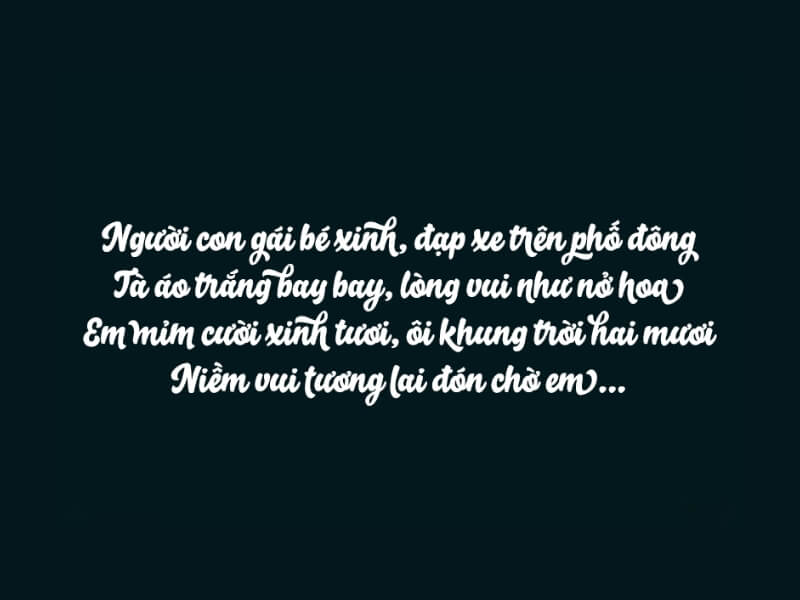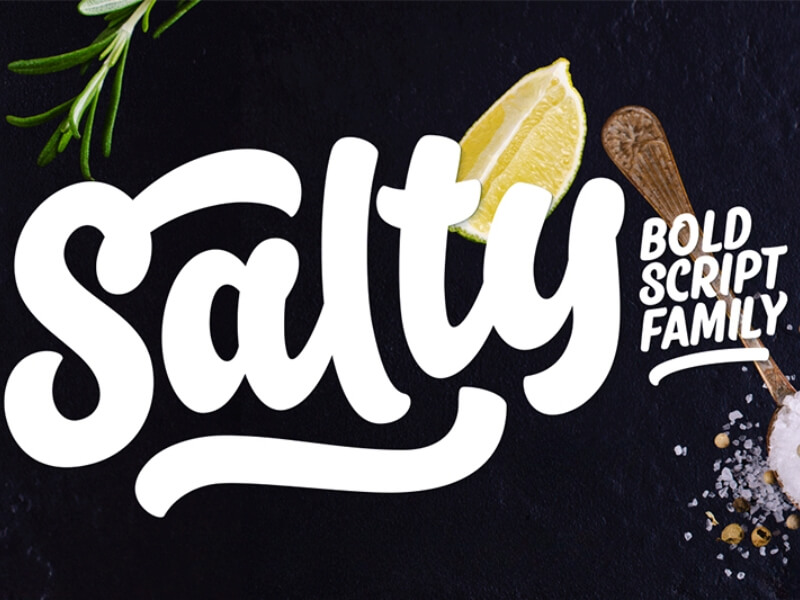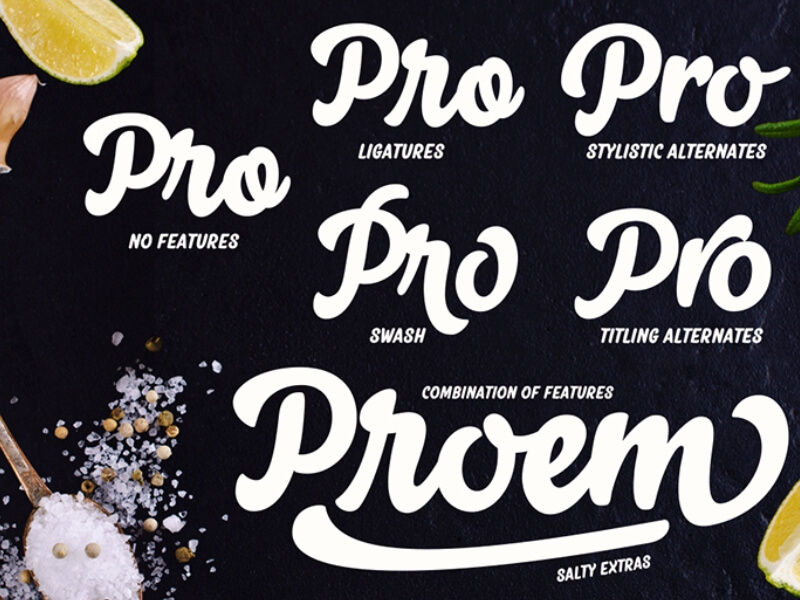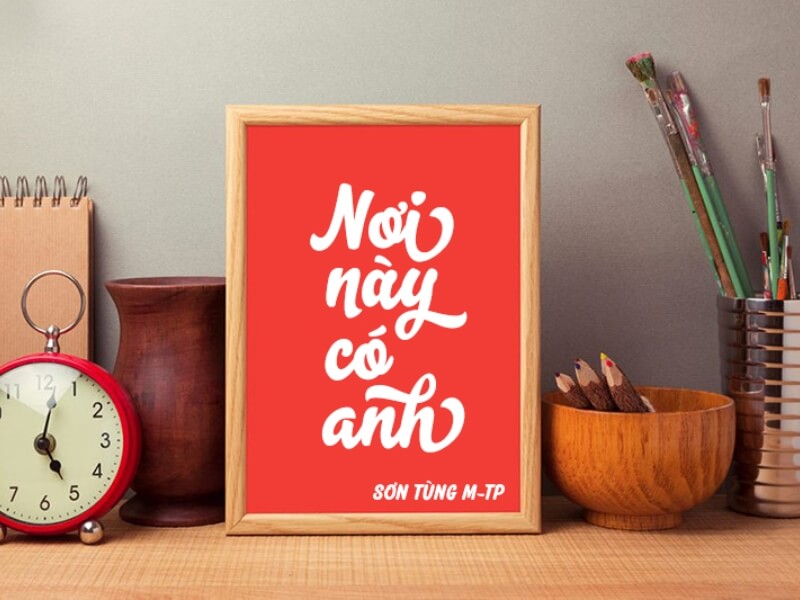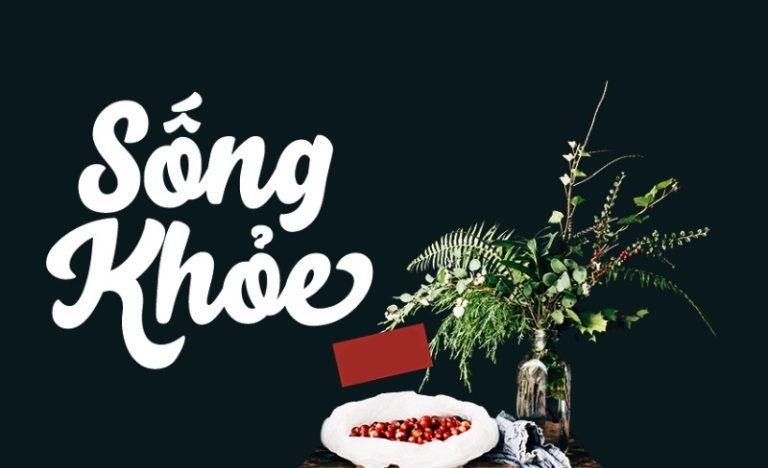
Font Việt hóa SVN Salty Script mang phong cách brush script với những đường nét thô mộc, tạo cảm giác như được viết bằng cọ vẽ đầy ngẫu hứng. Đây là bộ font chữ sở hữu nguồn năng lượng trẻ trung, phóng khoáng, phù hợp cho những dự án thiết kế hướng đến sự tự nhiên và gần gũi. Thư viện tài nguyên của BCD House chia sẻ bộ font này nhằm hỗ trợ cộng đồng kiến trúc và thiết kế có thêm lựa chọn chất lượng để làm mới các ấn phẩm đồ họa cũng như nhận diện thương hiệu.
Khám phá vẻ đẹp phóng khoáng của font Việt hóa SVN Salty Script
Điểm thu hút của SVN Salty Script nằm ở cấu trúc chữ không quá gò bó, các nét đậm nhạt được xử lý khéo léo như vệt mực loang trên giấy. Khác với các dòng font script thanh mảnh, Salty Script mang đến vẻ ngoài dày dặn, vững chãi nhưng vẫn giữ được sự linh hoạt cần có. Việc sử dụng bộ font Việt hóa SVN này giúp các designer hạn chế tình trạng lỗi hiển thị ký tự đặc trưng trong tiếng Việt, giúp quy trình làm việc trở nên thuận tiện hơn.
Bản Việt hóa đã được tinh chỉnh để các dấu thanh phối hợp hài hòa với độ cao của từng ký tự. Nhờ đó, tổng thể văn bản sau khi trình bày mang lại cảm giác cân đối, dễ nhìn và có tính thẩm mỹ cao. Đây là yếu tố quan trọng giúp nâng cao hiệu quả thị giác cho người xem trong các bản vẽ phối cảnh hoặc thiết kế bao bì sản phẩm.
Tư vấn phối màu: SVN Salty Script thường phát huy hiệu quả thị giác cao khi sử dụng các tông màu đất, xanh rêu hoặc các màu pastel trên nền trung tính. Bạn nên giữ nguyên nét chân thực của vệt cọ vẽ bằng cách hạn chế các hiệu ứng đổ bóng quá phức tạp.
03 Ứng dụng font Việt hóa SVN vào không gian kiến trúc
Với đặc tính nghệ thuật và sự tự nhiên, SVN Salty Script được nhiều kiến trúc sư và chủ đầu tư ưa chuộng để tạo điểm nhấn cho các công trình mang tính chất thư giãn:
- Bảng hiệu Homestay ven biển hoặc vùng núi: Phong cách brush của font chữ này rất ăn ý với các vật liệu tự nhiên như gỗ, đá hay mây tre lá. Đây là lựa chọn phù hợp cho biển hiệu các khu nhà lắp ghép, homestay container giúp tạo cảm giác mộc mạc và thân thiện cho du khách.
- Ấn phẩm truyền thông cho dự án nghỉ dưỡng: Sử dụng Salty Script cho các tiêu đề trên brochure, banner quảng cáo giúp khơi gợi cảm hứng về một không gian sống tự do, không khuôn khổ, rất dễ tạo thiện cảm với khách hàng.
- Trang trí nội thất và Quotes treo tường: Bạn có thể dùng font chữ này để cắt decal hoặc uốn đèn led trang trí trong các căn hộ, văn phòng hiện đại. Nét chữ mềm mại giúp làm dịu đi sự thô cứng của các cấu trúc thép hay mảng tường bê tông phẳng trong công trình.
03 Lưu ý để khai thác font Việt hóa SVN Salty Script hiệu quả
Để đạt được hiệu quả thẩm mỹ như mong muốn khi làm việc với dòng font brush script, người dùng nên lưu tâm một số điểm sau:
- Hạn chế sử dụng toàn bộ chữ in hoa: SVN Salty Script có các nét nối đặc thù giữa chữ thường, việc viết hoa toàn bộ cụm từ dễ gây rối mắt và làm giảm khả năng nhận diện mặt chữ của người đọc.
- Lựa chọn kích thước hiển thị phù hợp: Do có nhiều chi tiết giả lập vệt mực thô, font chữ này nên được trình bày ở kích thước trung bình đến lớn. Ở kích thước quá nhỏ, các vệt cọ có thể bị nhòe, gây khó khăn cho việc quan sát.
- Kết hợp cùng các font tối giản: Để tạo ra sự cân bằng trong bố cục thiết kế, hãy phối Salty Script cùng một font chữ không chân (Sans Serif) đơn giản. Cách làm này giúp làm nổi bật tính nghệ thuật của tiêu đề mà vẫn giữ được sự chỉn chu cho tổng thể.